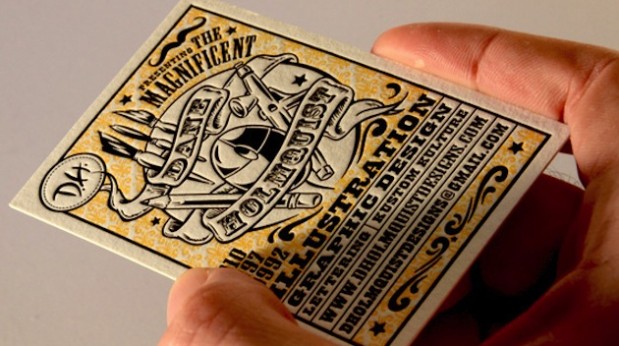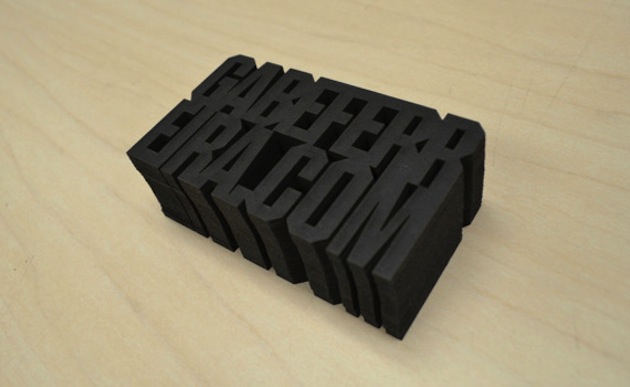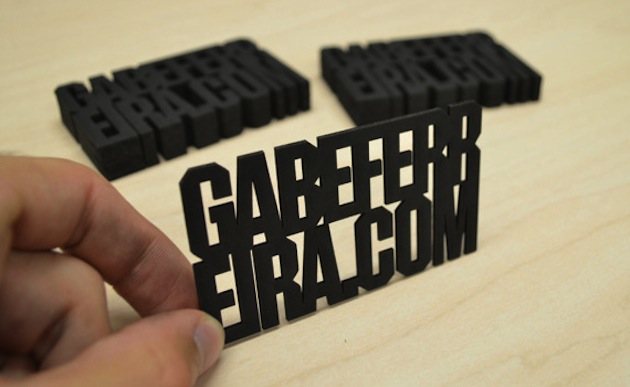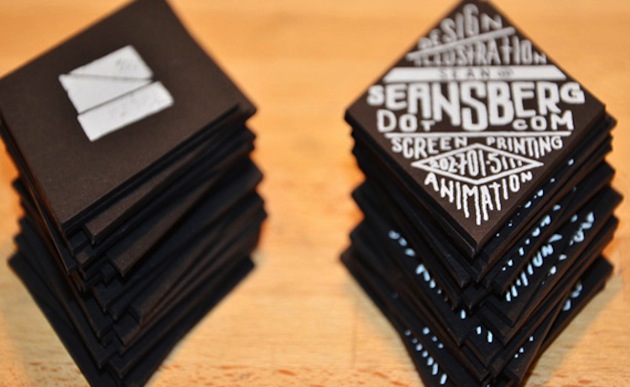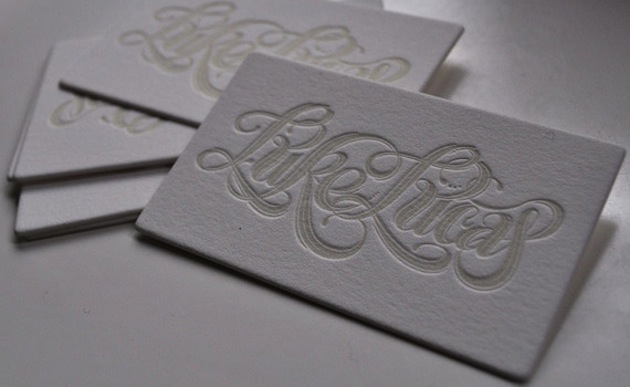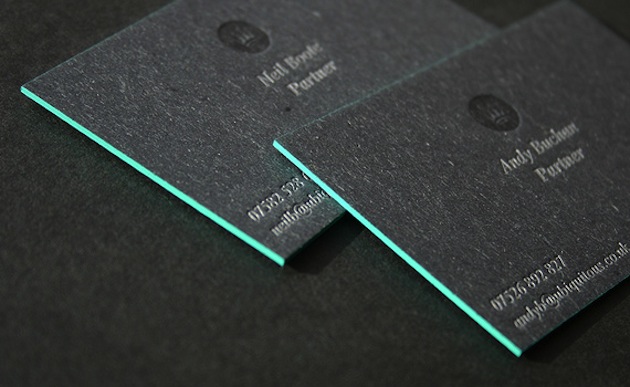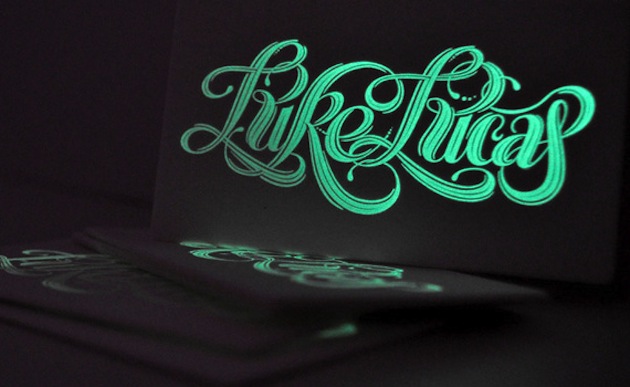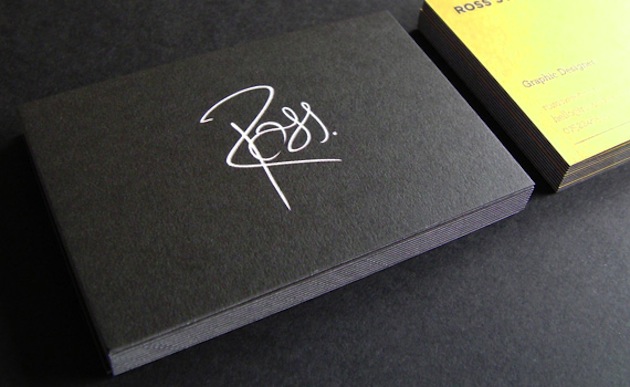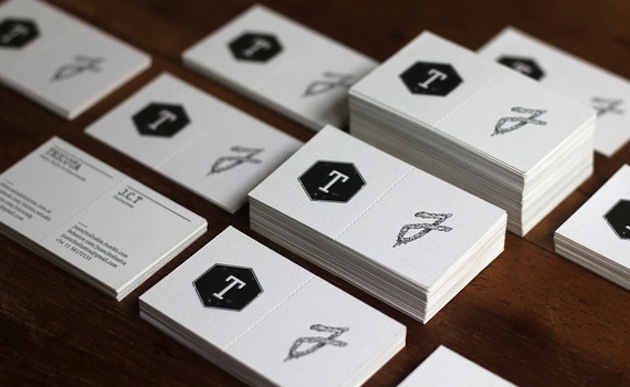
Ótimos meios de utilizar a tipografia em cartões de visitas
Cartões de visitas criativo para se inspirar e referenciar, fontes com auto relevo. (7)
2013 chegou e você ainda está usando aqueles cartões de visitas básicos, simples e padronizados.
Para que você não fique preso somente a esta ideia eu separei alguns cartões de visitas bem diferentes e criativos de alguns designer ou agências do mundo a fora para se referenciar, comece 2013 sendo a  diferença!
Nesta humilde seleção eu escolhi alguns cartões de visitas onde os designers fizeram um uso da tipografia ao extremo e com muita criatividade, veja que quando usamos uma fonte correta e um material bom o resultado é fantástico. Inspire-se!
Cartões de visitas criativo para se inspirar e referenciar, fontes com auto relevo. (1)
Cartões de visitas criativo para se inspirar e referenciar, fontes com auto relevo. (2)
Cartões de visitas criativo para se inspirar e referenciar, fontes com auto relevo. (3)
Cartões de visitas criativo para se inspirar e referenciar, fontes com auto relevo. (4)
Cartões de visitas criativo para se inspirar e referenciar, fontes com auto relevo. (5)
Cartões de visitas criativo para se inspirar e referenciar, fontes com auto relevo. (6)
Cartões de visitas criativo para se inspirar e referenciar, fontes com auto relevo. (7)
Cartões de visitas criativo para se inspirar e referenciar, fontes com auto relevo. (8)
Cartões de visitas criativo para se inspirar e referenciar, fontes com auto relevo. (9)